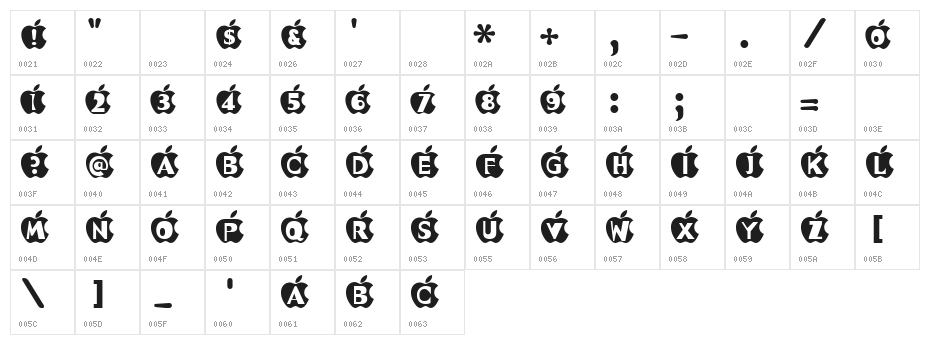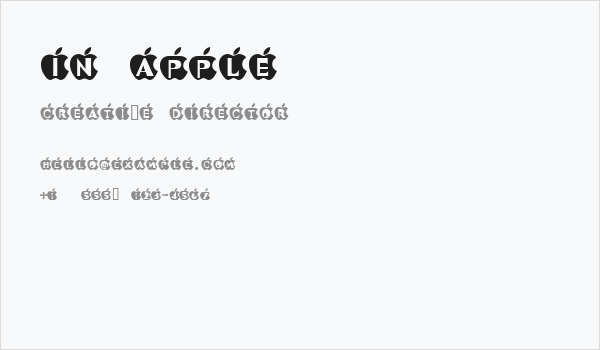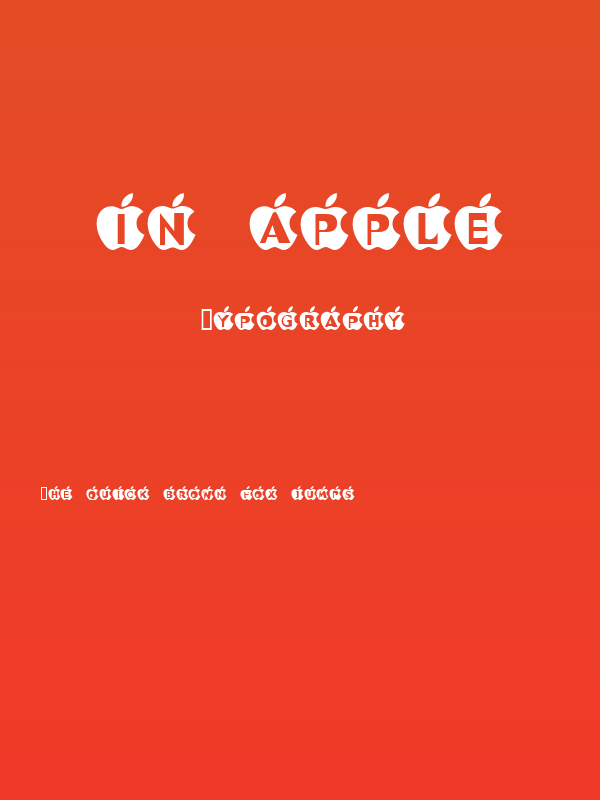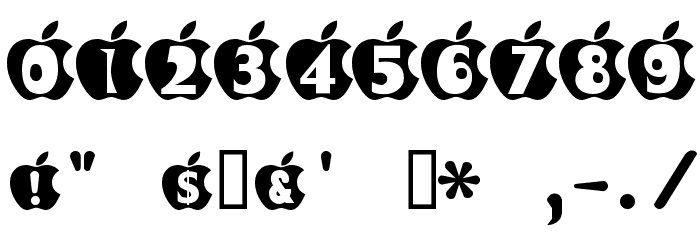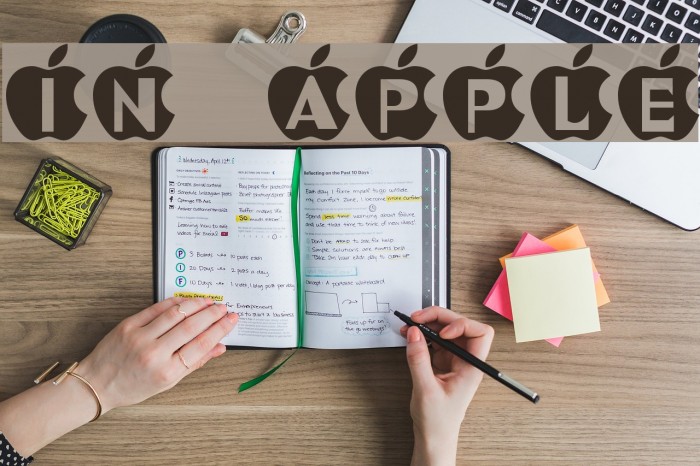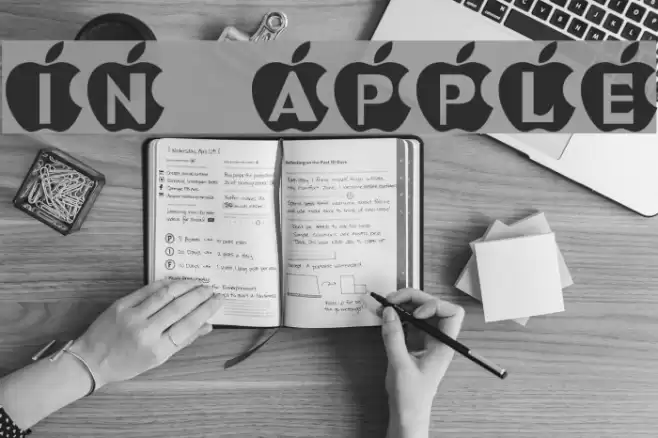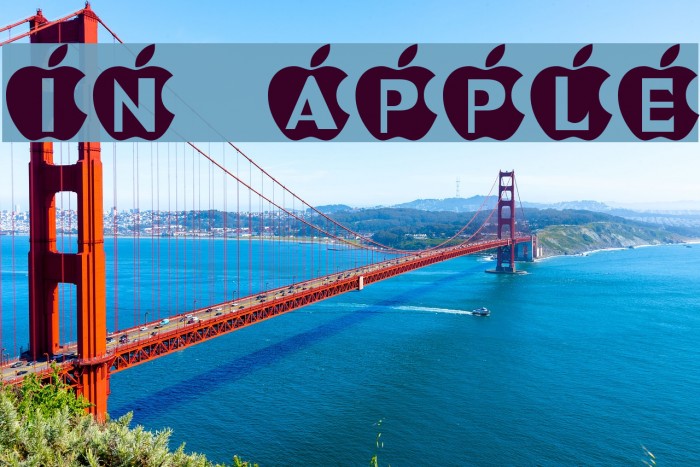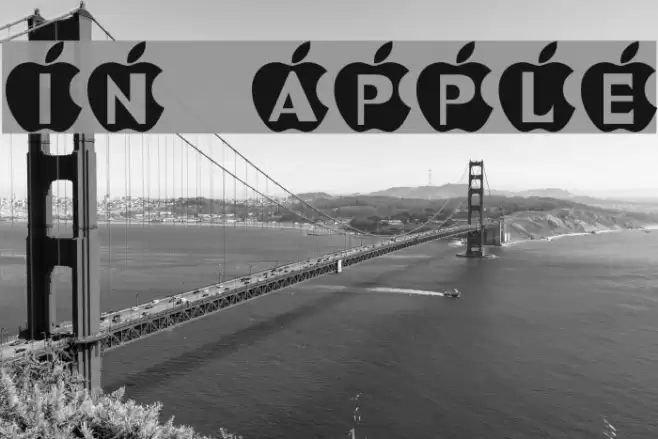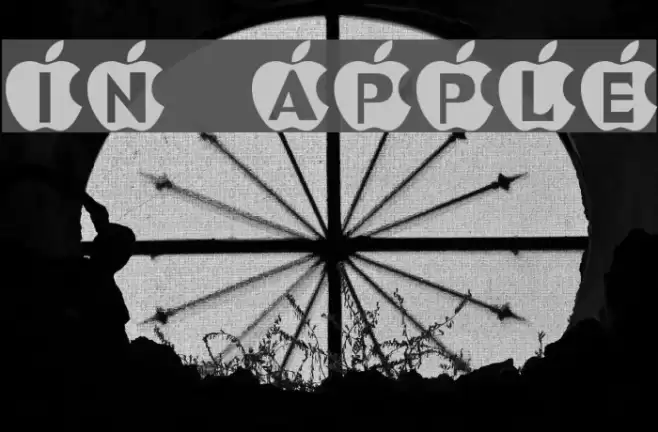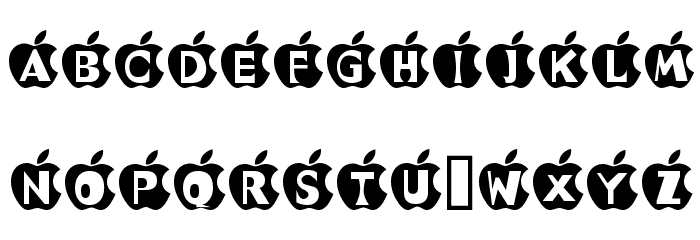
IN APPLE Font
✎ Decorative
| समग्र शैली | Modern, Playful |
| उपयोग का मामला | Logos, Headlines, Posters |
| सुझाए गए प्रोजेक्ट | Ideal for children's book covers, educational materials, playful branding, and promotional materials for events or products related to technology or fruit. |